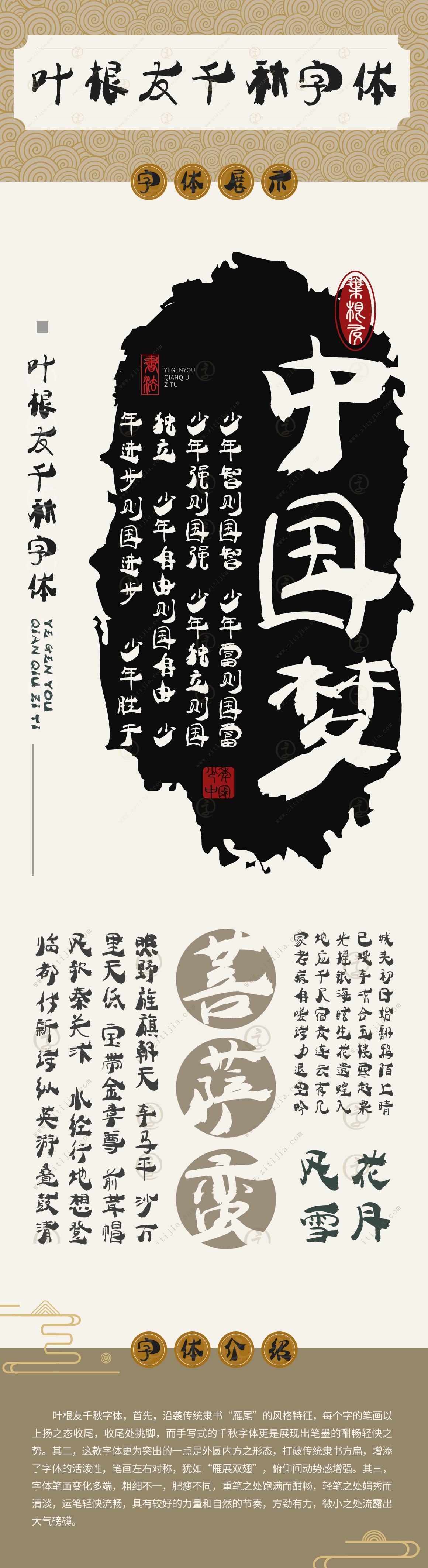
叶根友千秋字体
字体作者:叶根友
创作年代:2013年
字体介绍
叶根友千秋字体风格浑厚大气,延续隶书的风格特征进行创作,灵感来自韩国电视剧《千秋太后》之剧名书法“后”的风格,经过创意改变思维模式,创新了一款叶根友千秋字体作品,这个字体的风格特征是每个字的笔画尾部都上扬,浑厚而富有书法韵味,浓重之中展现了中国书法抑扬顿挫之运笔追求,是继蚕燕隶书之后又一毛笔隶书作品的发布。